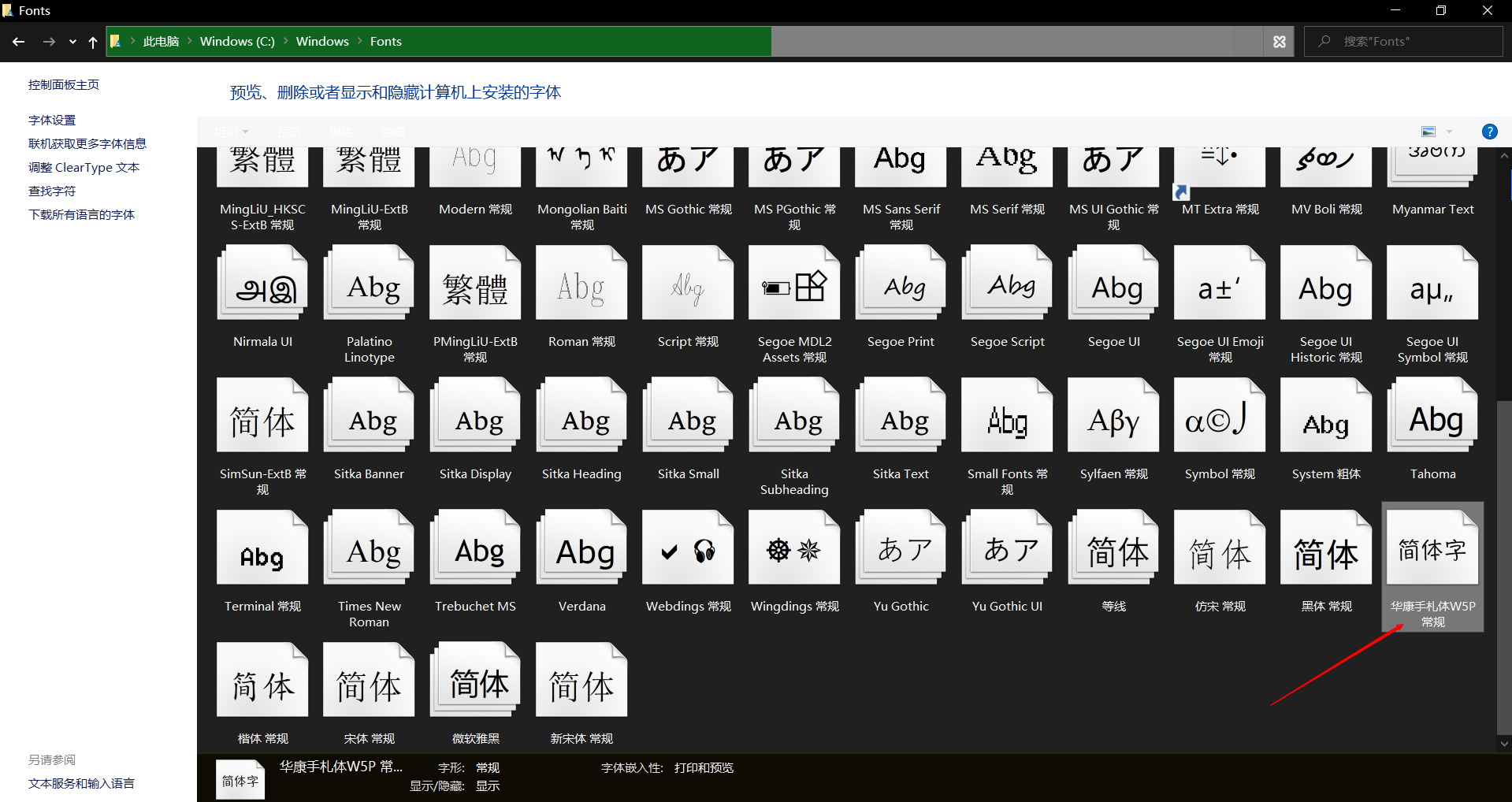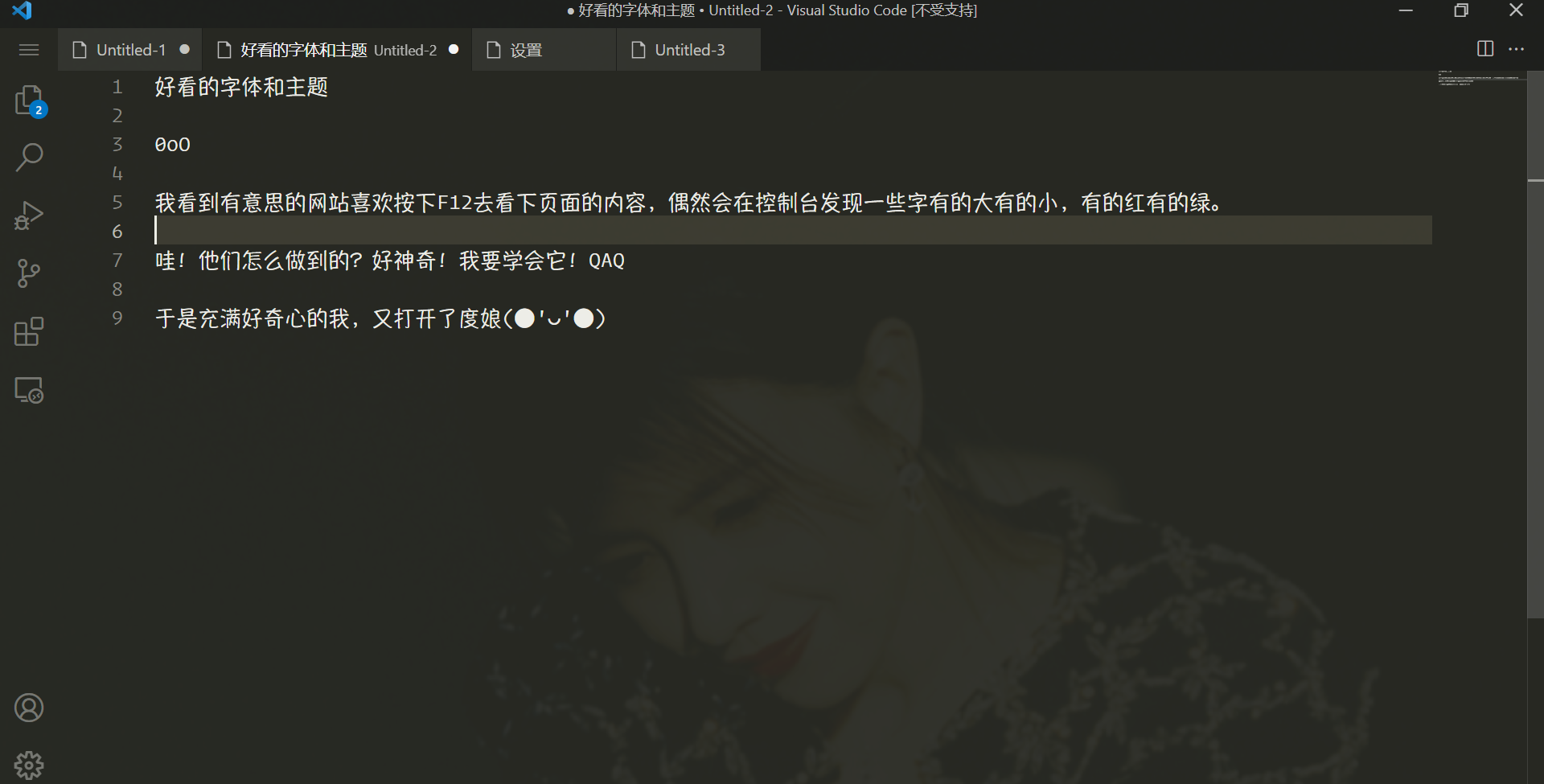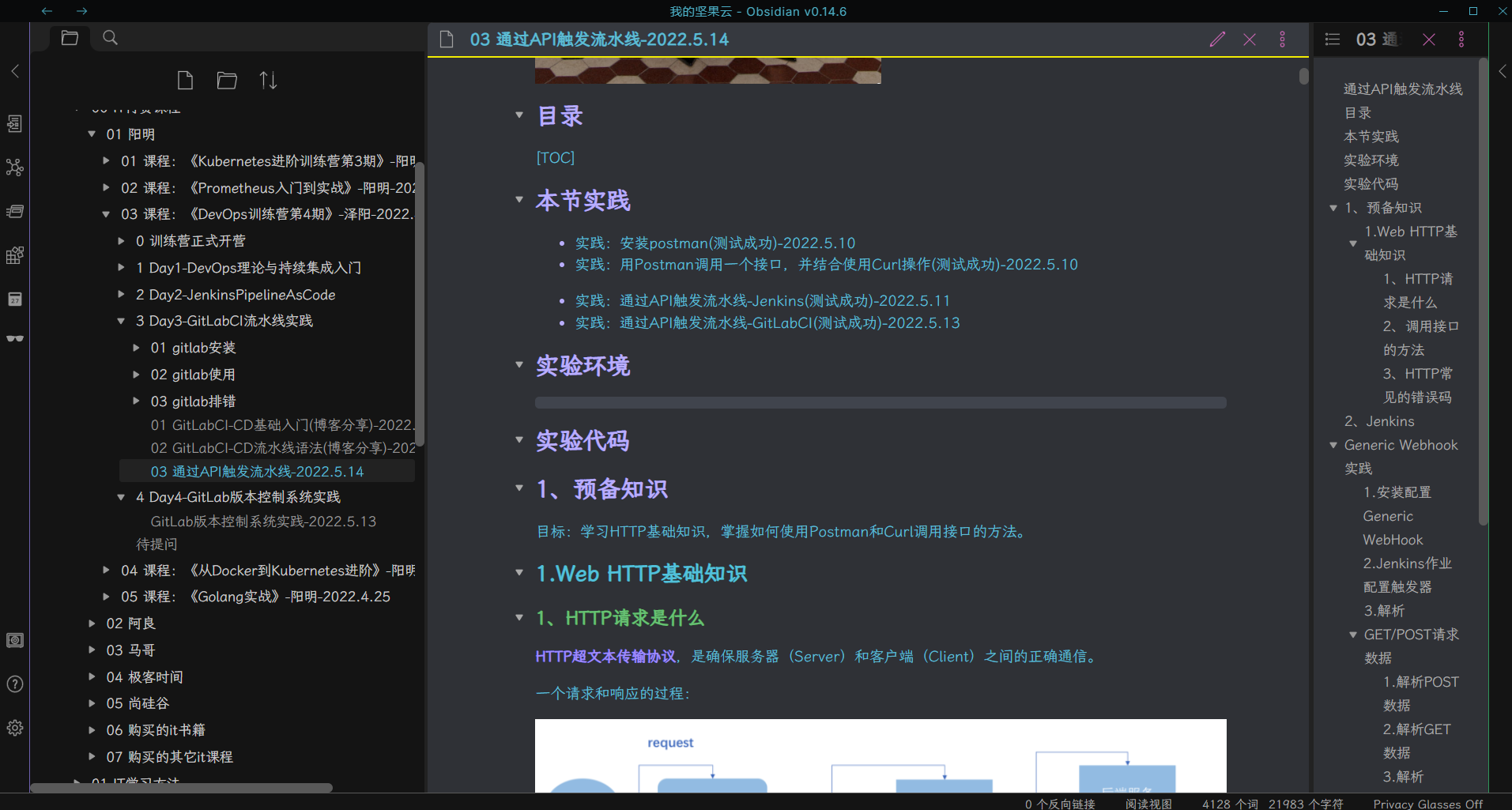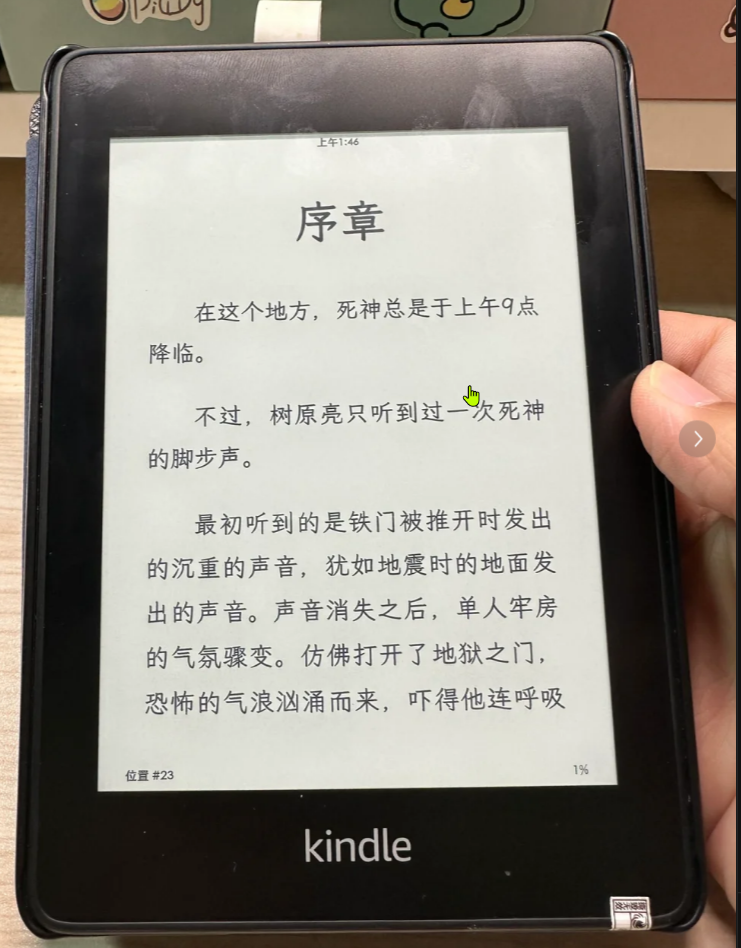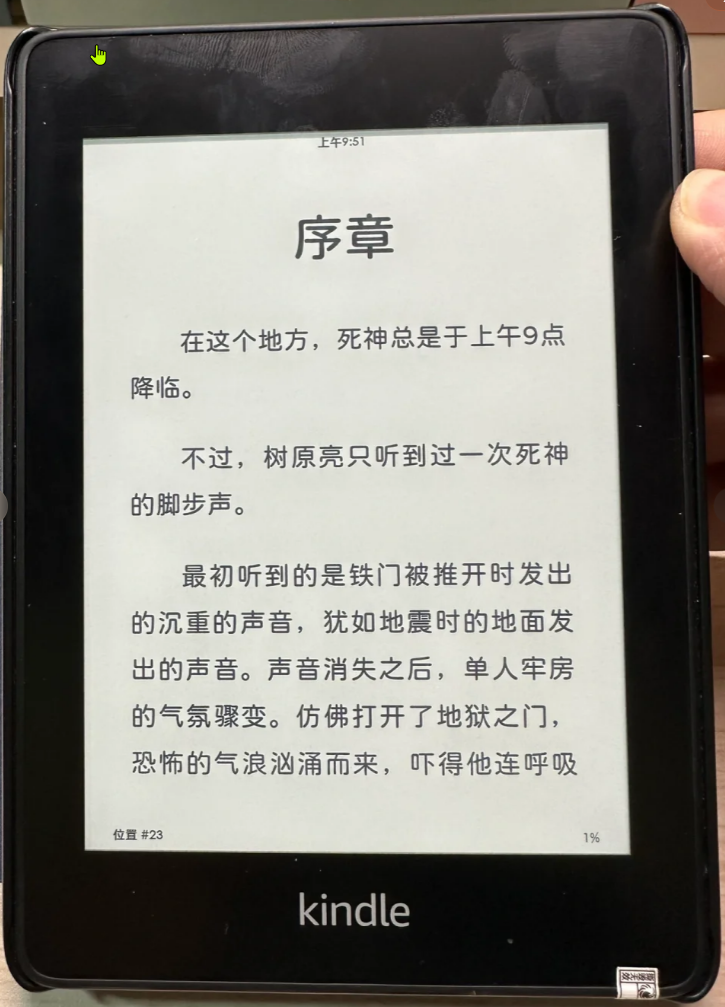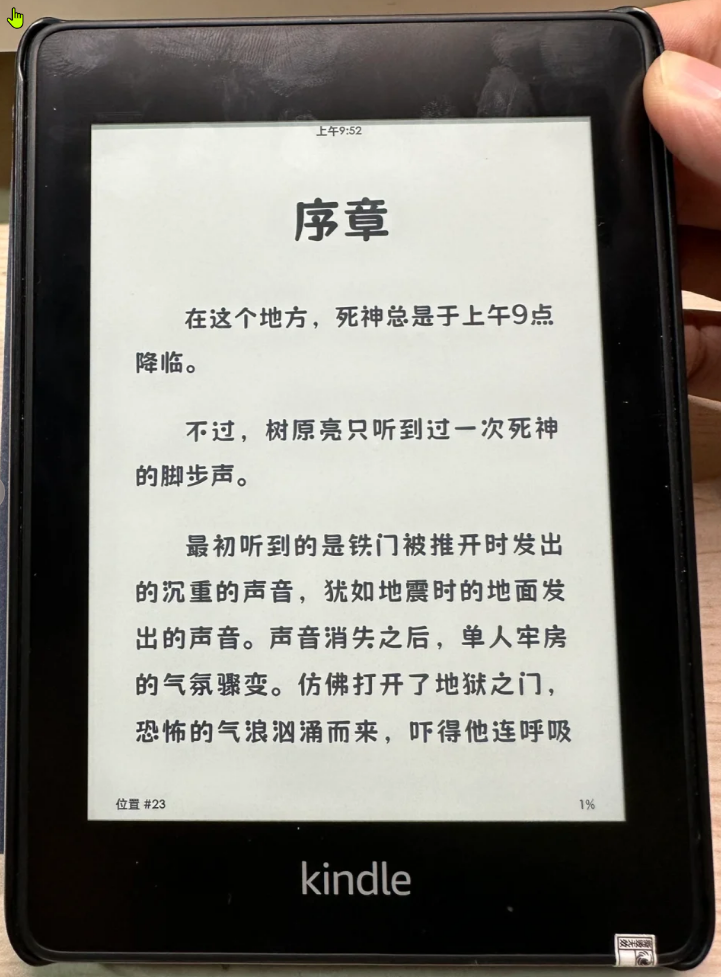
好看的中文字体
阿里巴巴普惠体
筑紫A丸
• 效果
HarmonyOS Sans
汉仪正圆
字体效果:
寒蝉全圆体
华康手札体W5P字体
hannotate是什么字体?hannotate sc regular字体又叫手札体 简常规标准体,这款字体字形清秀工整,线条流畅洒脱,笔形富于变化。
这个对中文来说是非常舒服的,效果如下:
霞鹜文楷
汉仪旗黑
森泽UD新黑
得意黑
筑紫 Pro
阿丽达黑体
方正可变悠黑
思源黑体
苍耳渔阳体
猫啃珠圆体